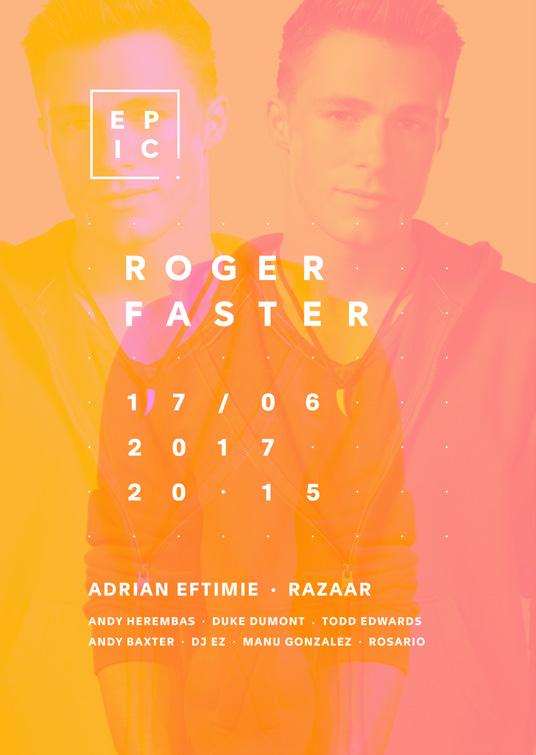
3 Čtverec označuje prostor klubu a tečka značí jeho vchod, tzn. vstup do epického prostoru. Základní logotyp EPIC je umístěn v černém čtverci s tečkou v rohu. Tečka se může přesouvat do všech rohů viz kapitola Umístění. V logu je použit font Apax, v řezu Bold.
4 Logo lze také použít v jiných tvarech nežli jen ve čtverci. Je možné jej přeskládat do podoby obdélníku, který lze použít jak ve vertikální tak horizontální verzi. Tečka se opět vyskytuje v rohu. V kterém rohu tečka bude určuje umístění loga viz kapitola Umístění loga.
5 Logo lze také použít v jiných tvarech nežli jen ve čtverci. Je možné jej přeskládat do podoby obdélníku, který lze použít jak ve vertikální tak horizontální verzi. Tečka se opět vyskytuje v rohu. V kterém rohu tečka bude určuje umístění loga viz kapitola Umístění loga.
6 Primárně se používají především černobílé verze. Nabízí se však i barevná varianta. Pro barevnou variantu lze používat pouze barvy z primární palety viz kapitola Barevnost. Při použití na bílém podkladu se barevně označují pouze písmena a tečka v rohu. Při použití na tmavém podkladu se barevně označuje pouze čtverec bez tečky.
7 Primárně se používají především černobílé verze. Nabízí se však i barevná varianta. Pro barevnou variantu lze používat pouze barvy z primární palety viz kapitola Barevnost. Při použití na bílém podkladu se barevně označují pouze písmena a tečka v rohu. Při použití na tmavém podkladu se barevně označuje pouze čtverec bez tečky.
8 Primárně se používají především černobílé verze. Nabízí se však i barevná varianta. Pro barevnou variantu lze používat pouze barvy z primární palety viz kapitola Barevnost. Při použití na bílém podkladu se barevně označují pouze písmena a tečka v rohu. Při použití na tmavém podkladu se barevně označuje pouze čtverec bez tečky.
9 Primárně se používají především černobílé verze. Nabízí se však i barevná varianta. Pro barevnou variantu lze používat pouze barvy z primární palety viz kapitola Barevnost. Při použití na bílém podkladu se barevně označují pouze písmena a tečka v rohu. Při použití na tmavém podkladu se barevně označuje pouze čtverec bez tečky.
10 Dle volného prostoru můžeme vybrat logo jak čtvercové tak vertikální či horizontální. Vždy je však preferovaná základní čtvercová verze. Tečka se umísťuje dle zarovnání loga. Např. pokud je logo umístění do horního levého rohu, tečka se vyskytuje ve zcela opačném směru v pravém dolním rohu atp. Pokud se logo umísťuje na střed tak se používá verze s tečkou v pravém dolním rohu.
11 Ochrannou zónu loga určuje písmeno E a to sice v jeho výšce.
14 PLUM ANDROID GREEN MANDARIN C 56 M 85 Y 17 K 4 R 133 G 63 B 126 # 853F7E C 38 M 1 Y 83 K 0 R 178 G 204 B 74 # B2CC4A C 0 M 62 Y 76 K 0 R 242 G 124 B 65 # F27C41 V sekundární barevné paletě nalezneme tři barvy Plum (vínová), Android Green (světle zelená) a Mandarin (oranžová). Ačkoliv jsou barvy ze základní palety preferované je samozřejmě možné použít pro branding barvy ze sekundární palety. PANTONE 689 C PANTONE 375 C PANTONE 164 C Barvy se liší svou barevností v digitální verzi a v tiskové verzi. V tiskové verzi jsou barvy lehce tlumenější. Pokud je nutné aby tiskové materiály měly výraznou barvu, je možné použít definované Pantone barvy.
15 Aa Bb Cc Základním fontem v kterém je uveden samotný logotyp EPIC je font Apax. Jedná se o geometrický, moderní, bezpatkový font. Tento font je používán napříč celým brandingem a používá se pouze ve dvou řezech Bold a Regular. Řez Bold se používá pro veškeré headliny, řez Regular naopak jen pro delší text v odstavcích apod. A B C D E F G I J K L M N O P Q R S T U V W Y Z a b c d e f g i j k l m n o p q r s t u v w x y z ! # " $ % & ( ) { } ~ * +, : ; A B C D E F G I J K L M N O P Q R S T U V W Y Z a b c d e f g i j k l m n o p q r s t u v w x y z ! # $ % & ( ) { } ~ * +, : ;
16 Aa Bb Cc Pouze v krajních případech kdy není možné z technických důvodů použít font Apax je možné jej nahradit fontem Arial. A B C D E F G I J K L M N O P Q R S T U V W Y Z a b c d e f g i j k l m n o p q r s t u v w x y z ! # " $ % & ( ) { } ~ * +, : ; A B C D E F G I J K L M N O P Q R S T U V W Y Z a b c d e f g i j k l m n o p q r s t u v w x y z ! # $ % & ( ) { } ~ * +, : ;